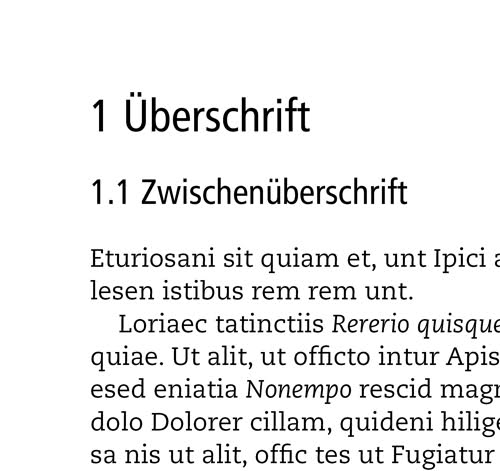
Schriften für medizinischen Ratgeber
ich soll für einen Kunden einen alternativen medizinischen Ratgeber zum Thema "Schmerztherapie" setzen.
Seine Vorstellung ist eine gut lesbare und modern wirkende Schrift. Serifen oder nicht Serifen ist noch offen bzw. hängt vom Gesamteindruck ab. Auf keinen Fall soll ein Lehrbuch-Charakter entstehen.
Erschwerend kommt hinzu, dass die Überschriften 1. Ordnung sehr kurz sind (minimal vier Buchstaben), die Überschriften 2. Ordnung aber überwiegend sehr lang (oft zwischen 120 und 130 Zeichen).
Ich habe zwar schon einiges ausprobiert: Garamond mit Syntax, Gill Sans, Frutiger; Palatino mit Avant Garde; Trump Mediäval mit Lucida Sans, Optima; Utopa mit Helvetica, Vera Sans, Eurostile. Gefällt mir alles nicht, weil es einfach unpassend und/oder langweilig aussieht.
Diese Versuche zeigen vermutlich schon, dass ich momentan noch eher ziellos herumstochere denn zielgerichtet probiere. Eine Suche hier im Forum hat mich leider auch nicht vorangebracht :(
Wenn Neukauf nicht in Frage kommt, ist es schwer zu beantworten, da niemand weiß welche Schriften zur Verfügung stehen.
Vor dem problem stehe ich nicht das erste Mal, trotzdem habe ich keine Idee, wie es sich lösen ließe. Einfach alle Schriften aufzuzählen, die ich besitze, wäre wohl eher kontraproduktiv.
Ansonsten stöbere auf Fontsquirrel. Und vergiss die erweiterte Vollkorn nicht.
Stimmt, Althausen hat die Vollkorn zwischenzeitlich weiter ausgebaut. Da ich momentan wohl mit der Regular und Italic hinkommen würde und auch keine unüblichen Zeichen benötige, werde ich mit ihr mal ein paar Seiten setzen.
Für die Überschriften würde ich aber gerne eine Serifenlose verwenden. Was würde denn dazu passen?
hast du die myriad? die mit garamond könnte doch gehen.
Stimmt, die Variante hatte ich auch noch probiert. Sah aber eben doch ebenfalls recht bieder aus. Und dann eben die Überschriften 2. Ordnung :(
Mir stellt sich da sofort die Frage, ob das »medizinisch« betont werden soll, oder das »alternativ«? Die Schriften dazu stelle ich mir dann jeweils etwas anders vor.
Wenn die Überschriften der zweiten Ordnung so lang sind, dann würde ich ja zu einem Condensed-Schnitt greifen.
Ideal ist es mit Sicherheit nicht, aber hast Du Dir die Lido STF mal angesehen? Die ist nicht so verstaubt wie die Times und es gibt sie in Regular, Medium & Bold, mit einem Condensed-Schnitt dazu. Eine der ökonomischsten Schriften die ich bisher in wissenschaftlichen Dokumenten eingesetzt habe. Ich persönlich würde dann dazu einen Schnitt einer schönen Serifenlosen kaufen, die es als Condensed-Schnitt gibt. Das aber auch nur weil mir bei den freien Schriften sonst nix dazu einfällt. :P
Mir stellt sich da sofort die Frage, ob das »medizinisch« betont werden soll, oder das »alternativ«? Die Schriften dazu stelle ich mir dann jeweils etwas anders vor.
Schwer zu sagen. Ich denke, die Betonung liegt eher auf alternativ.
Ideal ist es mit Sicherheit nicht, aber hast Du Dir die Lido STF mal angesehen? Die ist nicht so verstaubt wie die Times und es gibt sie in Regular, Medium & Bold, mit einem Condensed-Schnitt dazu.
Ja, aber leider nur für den nichtkommerziellen Gebrauch kostenlos :cry: Andererseits ist sie allerdings auch erschwinglich.
Ich persönlich würde dann dazu einen Schnitt einer schönen Serifenlosen kaufen, die es als Condensed-Schnitt gibt. Das aber auch nur weil mir bei den freien Schriften sonst nix dazu einfällt. :P
Von der Helvetica (bzw. einem Helvetica-Clone) gibt es einen, mit dem ich auch schon mal experimentiert habe. Aber zur Lido oder Vollkorn?
Wenn es eher alternativ sein soll, dann wäre mir die Lido zu ähnlich zur Times. Zu sachlich und zu neutral. Die PT Sans bzw. PT Sans Narrow würde ich ja mal ausprobieren; im Zweifelsfall zusammen mit Vollkorn und Lido und dann halt mal sehen wie es schaut. :roll:
Frutiger und Caecilia, anyone ...? :?
Wo gibt es die Caecilia für umsonst? WO? Sag schon! :D
Elseviers DNA Repair (Amsterdamm) hat eine Reihe von Jahren in der Caecilia gesetzt. Hat meiner Meinung nach gut funktioniert.
:hihi: Wird es nie geben, das traut sich keiner: Die Server würden unter der Downloadlast abrauchen ... ;) Aber ich weiß ja nicht, was der geschätzte Kollege HWP in seinem Schriftenköfferchen so an Schätzen hütet :D
so, der PC ist längst repariert (oder richtiger: ausgetauscht) zurück, aber der Kunde hatte es doch ziemlich eilig und sich deshalb auf die Kombination Garamond als Brotschrift und Helvetica (wegen des condensed Schnittes) für die Überschriften entschieden.
Meinen Vorschlag, die viel zu langen Überschriften zu kürzen, mochte er nicht aufgreifen. Ich finde das schade, weil es gut möglich gewesen wäre und das Buch dadurch nur gewonnen hätte, aber der Kunde ist König.